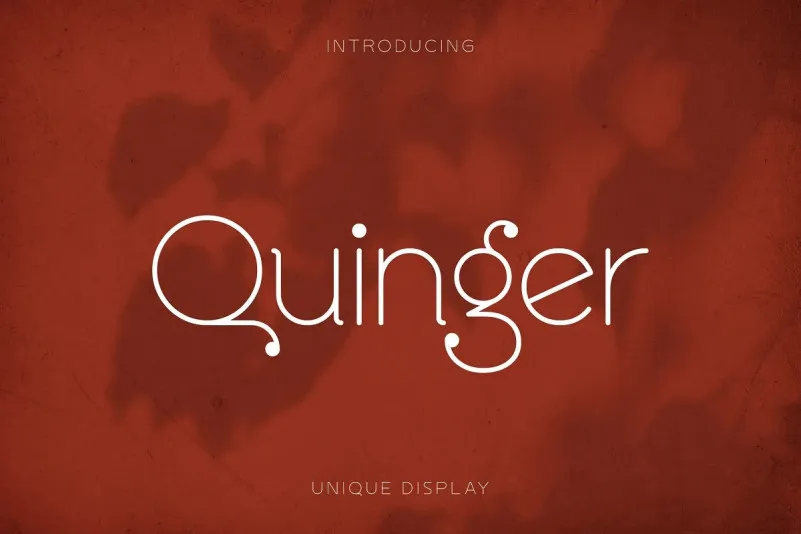
A Quinger Font é uma escolha ideal para designers que buscam dar um toque nostálgico às suas criações digitais sem perder a modernidade do tipo sans serif. Com sua característica serifa única, foi criada especialmente para trazer o encanto dos anos 50 e 60 para seus projetos. Esta fonte foi desenvolvida pelo Almarkha Type e incorpora linhas monolineárias que proporcionam um visual vintage perfeito, adequado tanto para criar templates de design impressos quanto brochuras digitais, videos promocionais ou até mesmo gráficos de marca. É uma excelente opção para os designers que estão buscando dar um toque pessoal e único às suas criações, tornando-a a escolha perfeita para personalizar logomarcas e outros elementos visuais de projetos de branding.